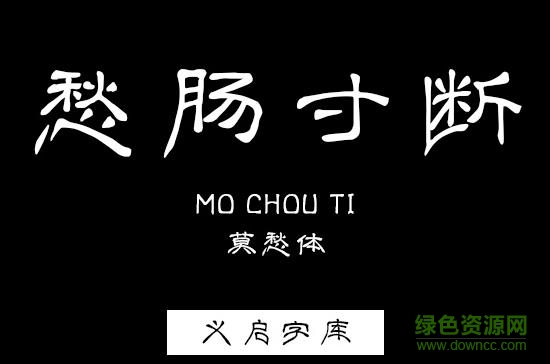
義啟莫愁體字體
義啟莫愁體是一款非常有特色的義啟字體,這款字體筆畫圓潤,結(jié)構(gòu)清晰簡約,看起來非常的舒服,喜歡這款字體的朋友可以來綠色資源網(wǎng)免費下載使用!
莫愁體字體簡介
莫愁前路無知己,天下誰人不識君。筆畫粗壯且粗細(xì)一律,起止皆方,氣象豐滿,筆畫質(zhì)感十足,簡約!
莫愁體